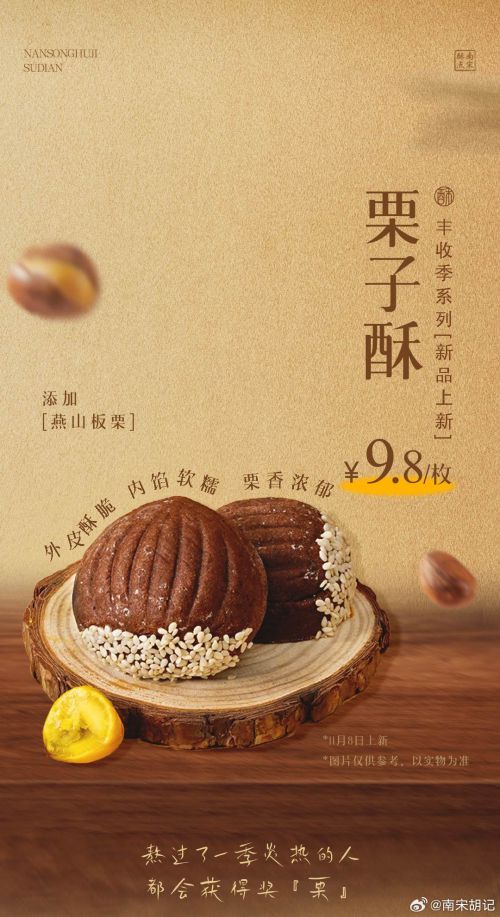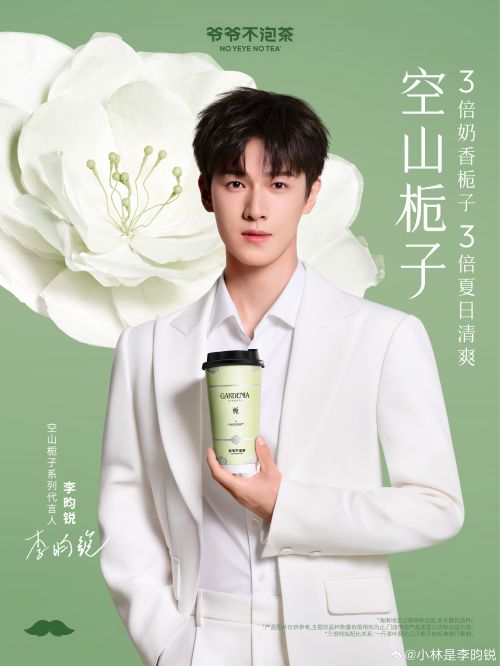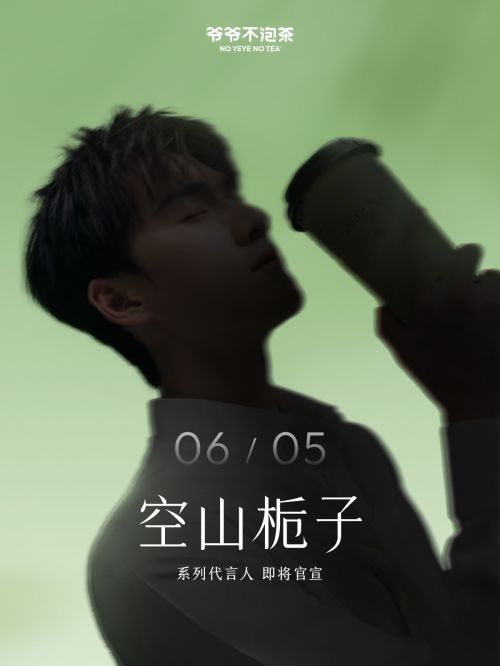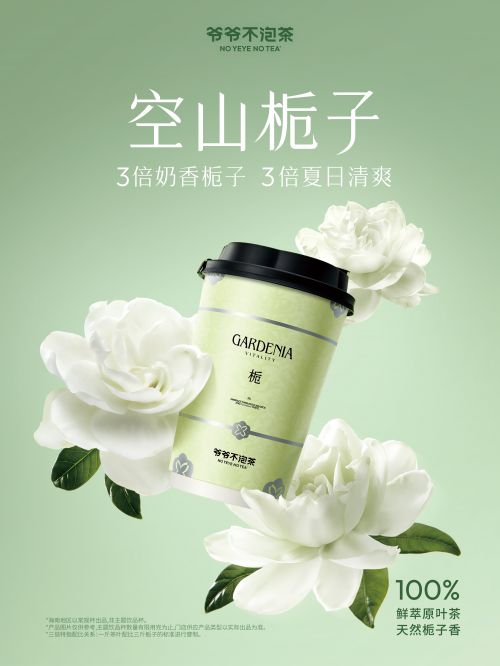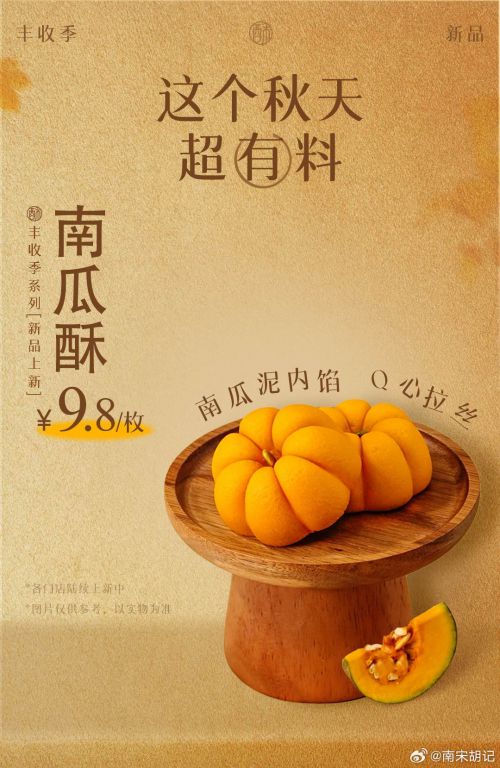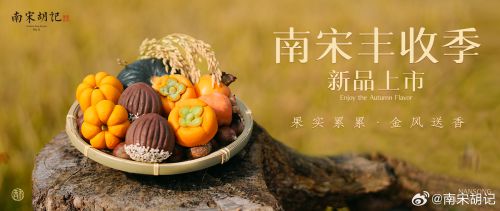
三极柔宋简体
字库品牌: 三极字库
三极中柔宋简体是一款非常漂亮的柔宋字体,其字形清新,布白均匀,字形结构饱满匀称、柔美,中宫偏大,笔形挺拔流畅,笔锋锐利简洁。个性鲜明,富有朝气。三极中柔宋简体风格清新醒目、时尚柔美,精致富有内涵,具有强烈的视觉冲击力。适用于传统印刷媒介的标题与正文排版。以及广告、标志和产品包装设计。